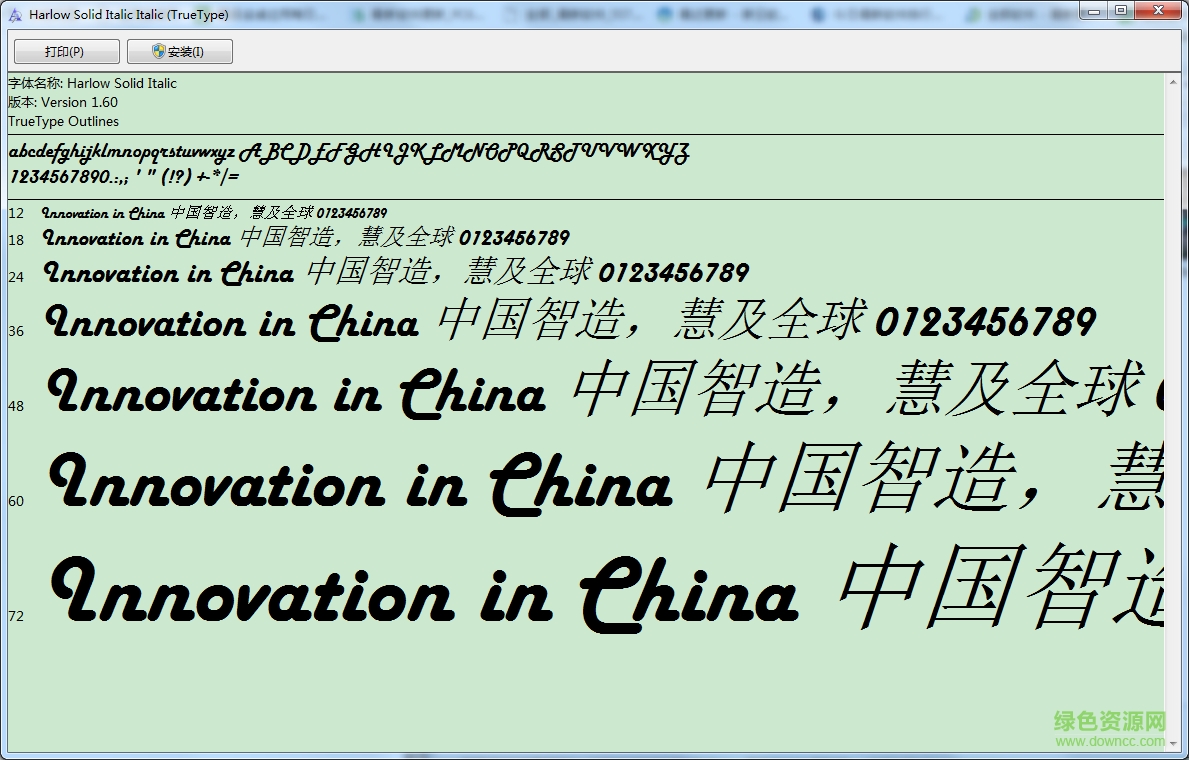
harlow solid italic是一款比較常用的英文字體,此款字體線條圓潤(rùn),大小粗細(xì)均勻,整體效果非常不錯(cuò),支持中文和英文輸入轉(zhuǎn)換,廣泛的應(yīng)用于廣告設(shè)計(jì)、平面設(shè)計(jì)等領(lǐng)域,歡迎來(lái)綠色資源網(wǎng)下載!
harlow solid italic字體是一款深受設(shè)計(jì)師喜愛(ài)的字體,此款字體具有一定的藝術(shù)感,易讀性非常強(qiáng),字體相對(duì)來(lái)說(shuō)比較完整,應(yīng)用范圍比較廣泛,喜歡的朋友歡迎來(lái)綠色資源網(wǎng)下載收藏!